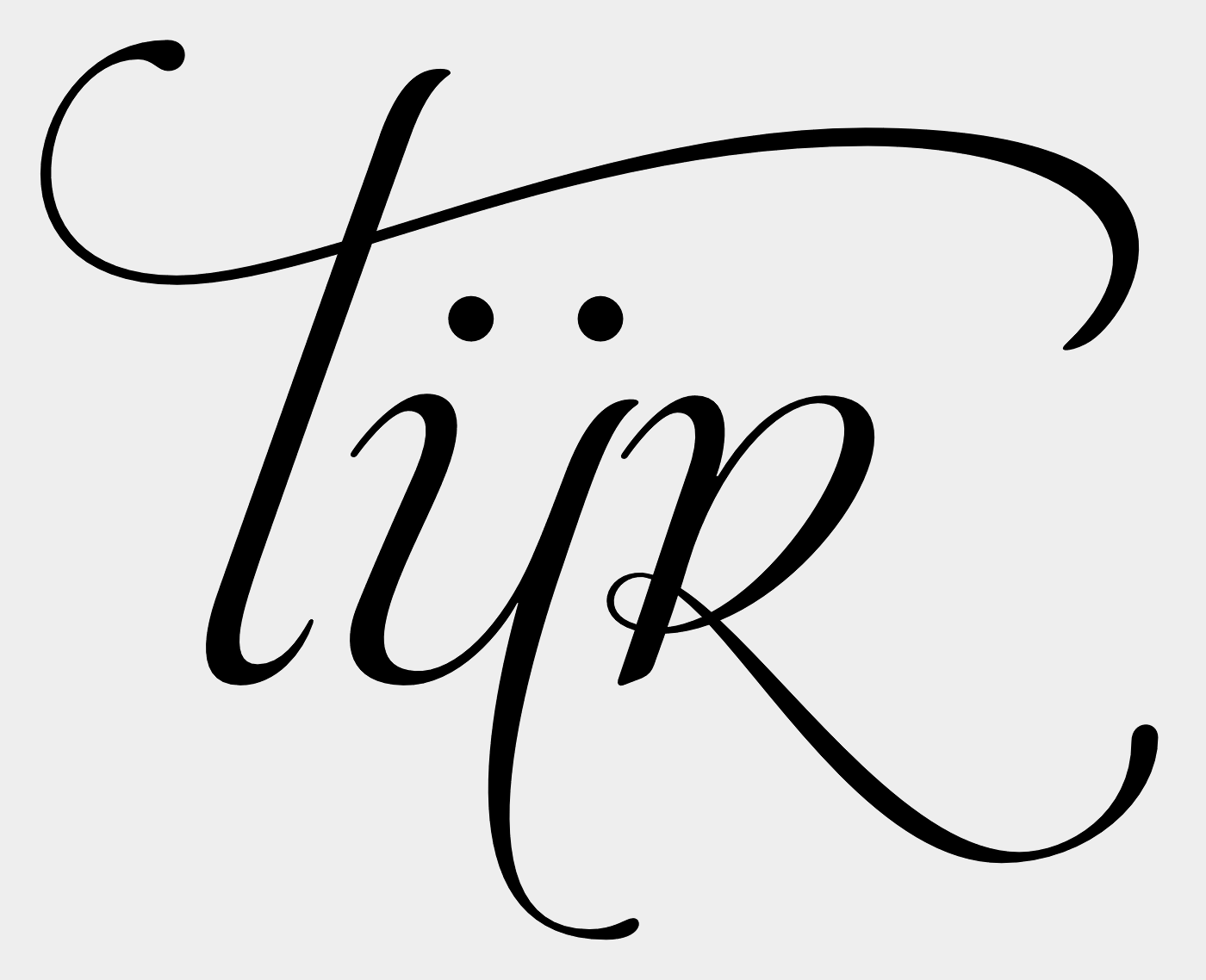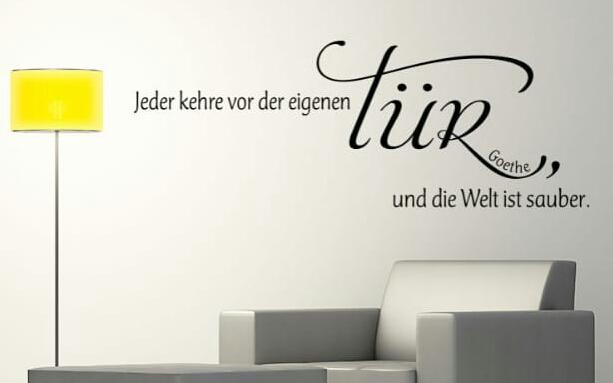
Welche Schrift ist das? (Wandtattoo)
wir müssen eine Schablone für einen Maler herstellen, die mit dem hochgeladenem Foto identisch ist...
Die Aphrodite gibt es in unterschiedlichen Versionen und Alternativbuchstaben, evtl. wurde da gemischt.
Miſt! Bertel war mal wieder schneller!  Club Type Std Light von Club Type ...
Typeface	: Club Type  - Originally called Mercurius.
Designer	: Adrian Williams
Year		: 1988
Publisher	: Adobe